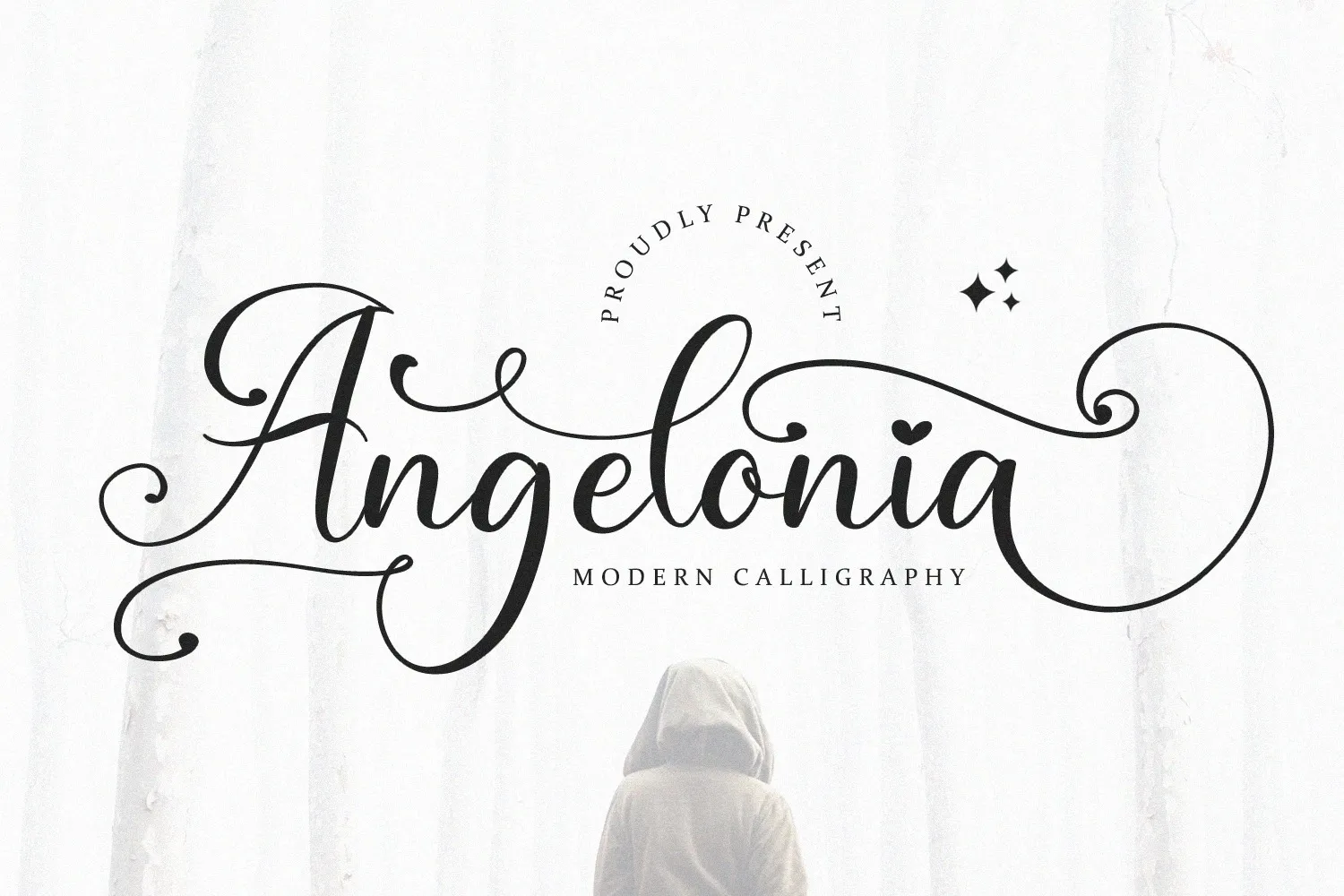
Angelonia Font
A Angelonia Font é uma elegante tipografia em estilo script criada pelo designer Naharstd. Especialmente projetada para capturar a atenção e trazer estilo à sua marca, logo ou projeto de design, esta fonte tem um charme singular que faz dela uma opção perfeita para várias aplicações. Seja para branding, criação de logotipos, letras personalizadas ou até mesmo para embalagens, as Angelonia Fonts são ideais para designers gráficos em busca de uma fonte única e sofisticada. Sua versatilidade é impressionante – desde o design de logomarcas e etiquetas para roupas, passando por posters, revistas e camisetas personalizadas, até as capas de livros ou mesmo como um recurso visual em eventos especiais. Com a Angelonia Font, você pode trazer uma nova dimensão à sua arte gráfica com um toque moderno e sofisticado que certamente não passará despercebido. Experimente incorporar esta fonte na próxima peça de design para destacá-la entre os demais.